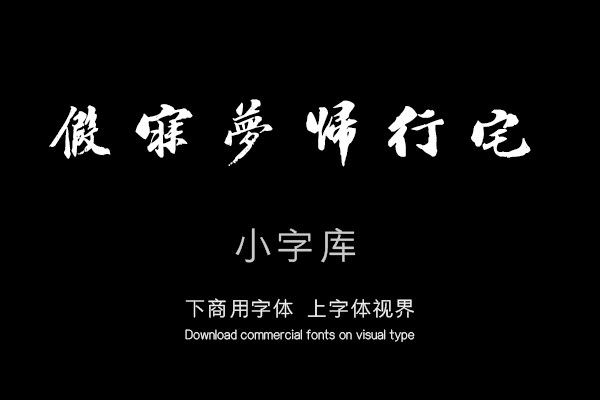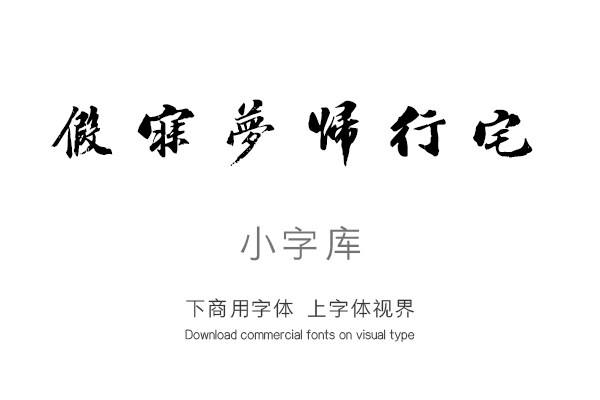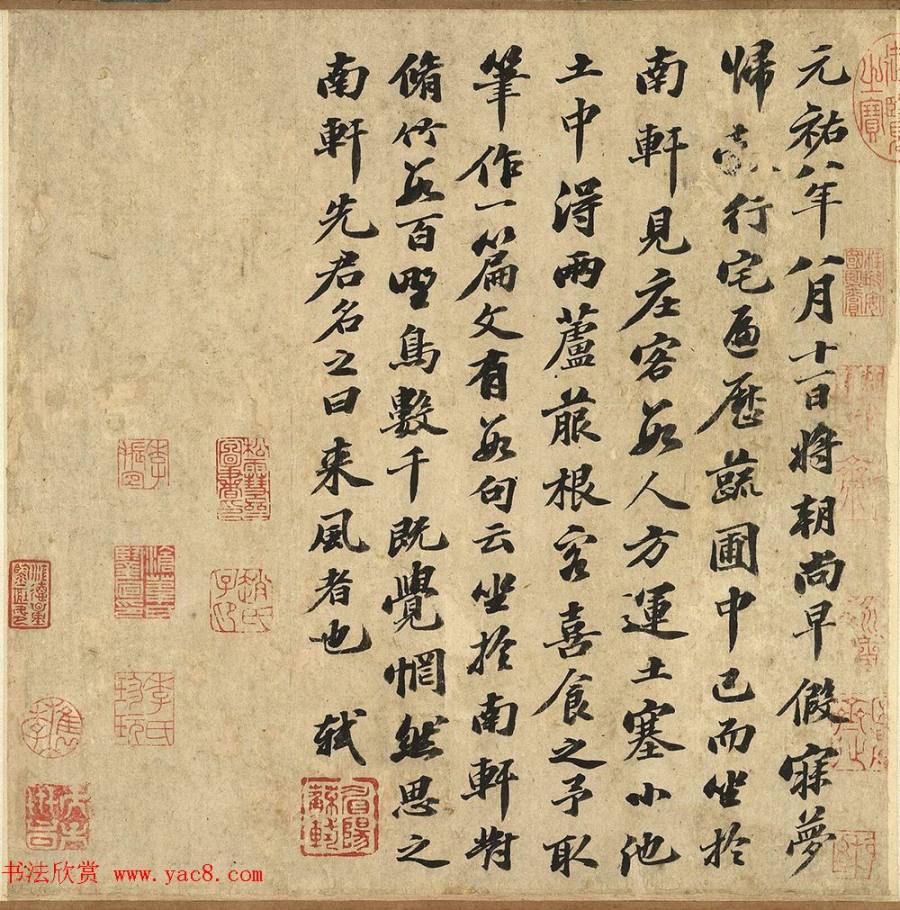
汉标苏轼南轩梦语
《汉标苏轼南轩梦语》是一款根据苏轼经典书法作品《南轩梦语》,经过再次调整制作的小字库,该小字库共收录了该真迹作品中约112个字体。
元祐八年八月十一日。将朝尚早。假寐梦归行宅。遍历蔬圃中。已而坐于南轩。见庄客数人。方运土塞小池。土中得两芦菔根。客喜食之。予取笔作一篇文。有数句云。坐于南轩。对修竹数百。野鸟数千。既觉惘然思之。南轩。先君名之曰来风者也。轼。